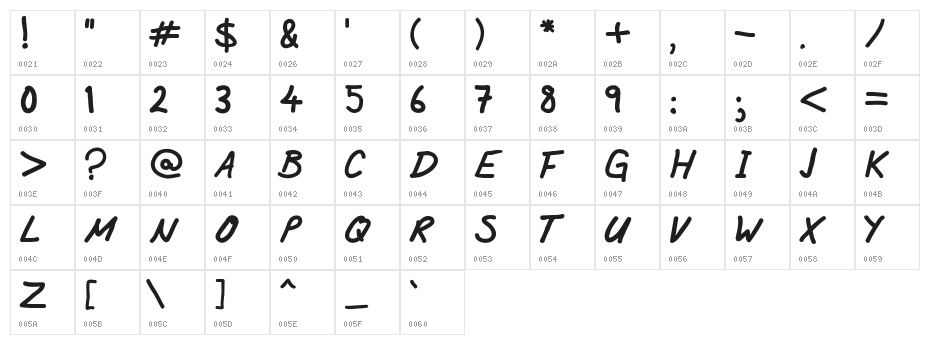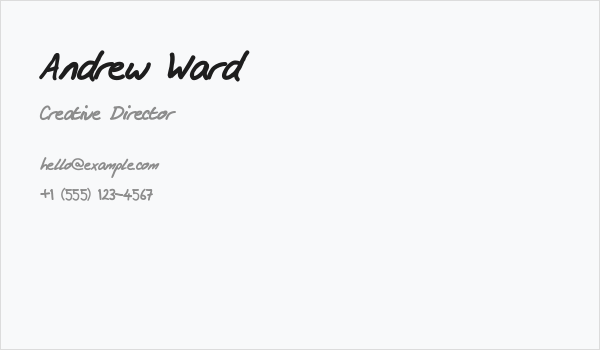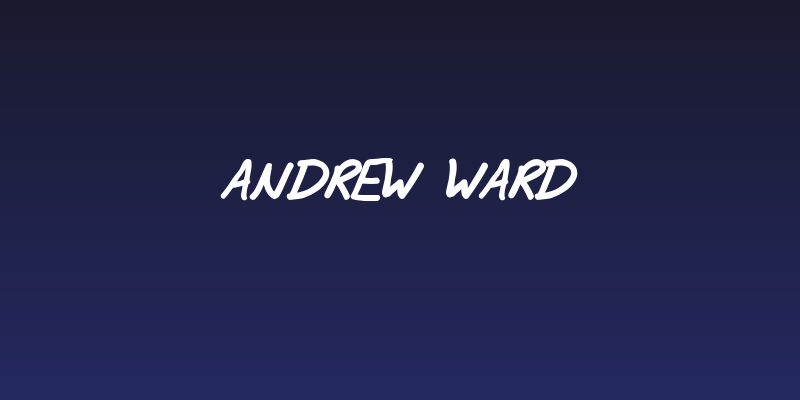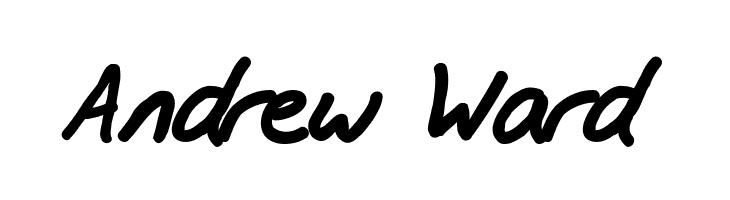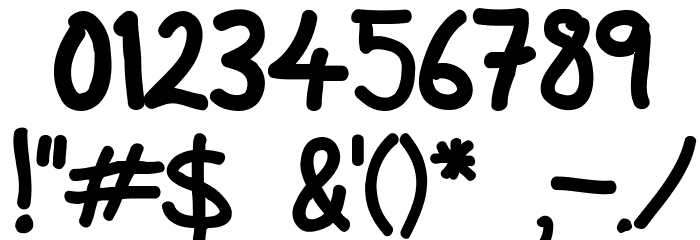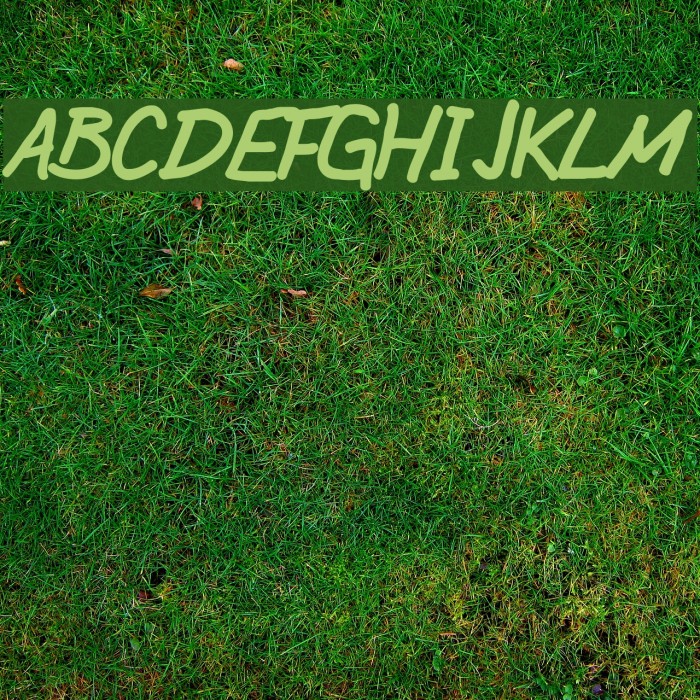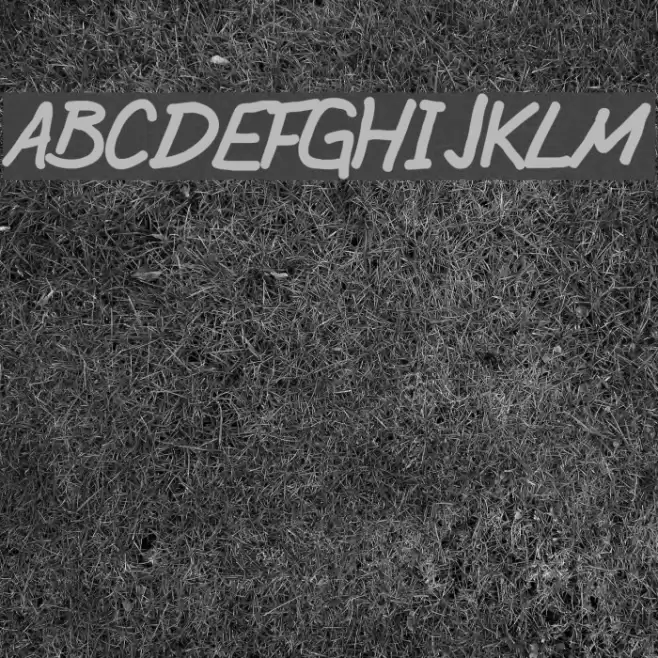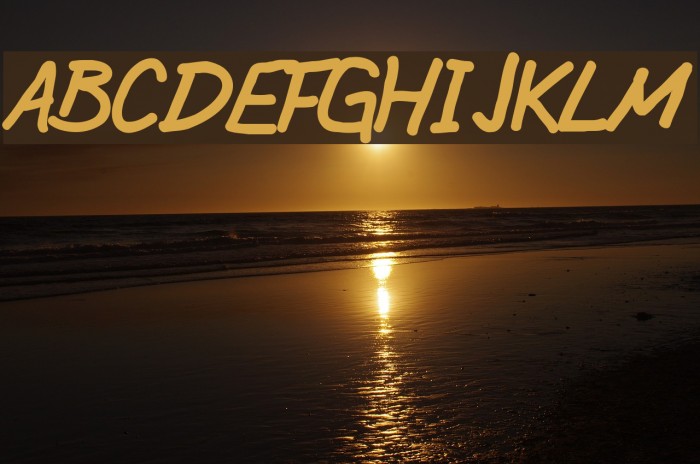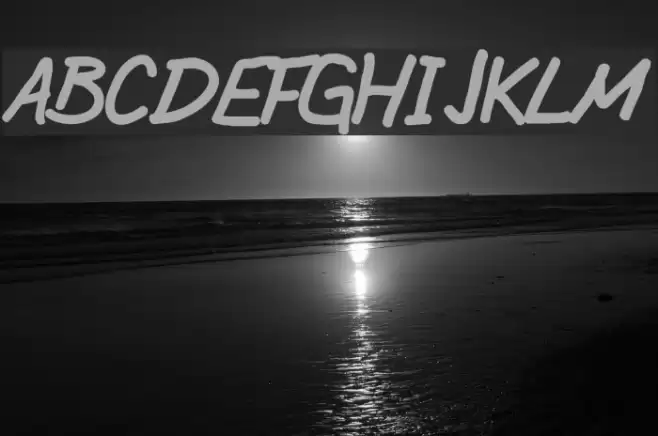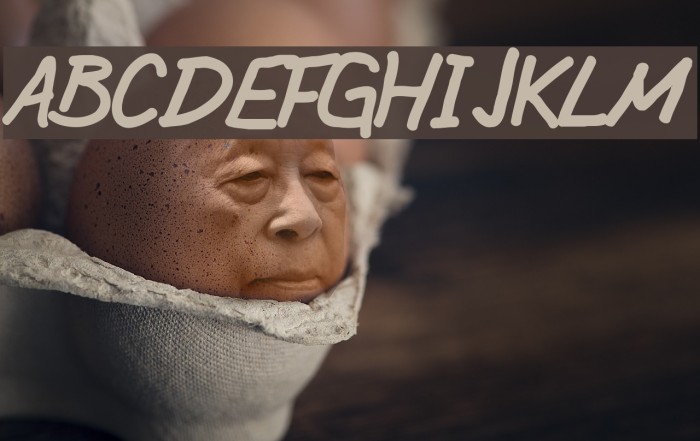
Andrew Ward Font
| Cas d'utilisation | Logos, Headlines, Informal Text |
| Projets proposés | Ideal for greeting cards, personal branding, social media graphics, and informal invitations. |